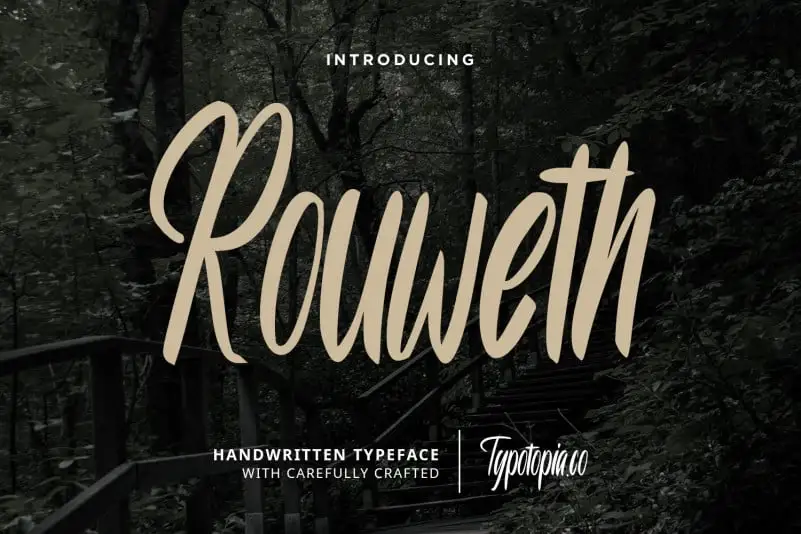
Rouweth Script Typeface – Download Grátis
A Rōweth Script Typeface é uma fonte tipográfica script que traz originalidade e fascínio para projetos criativos, especialmente quando se trata de design editorial. Essa elegante fonte foi pensada para personalizar logotipos, cartões de visita, embalagens de produtos, selos, cartazes e até mesmo roupas. Suas linhas fluidas e sutis são perfeitas para texturas variadas, como letras grandes em postais ou pequenas no conteúdo de etiquetas de alimentos. Ideal para criar uma identidade visual única, a Rōweth Script é um recurso indispensável para qualquer designer que busca expressar criatividade através da tipografia.